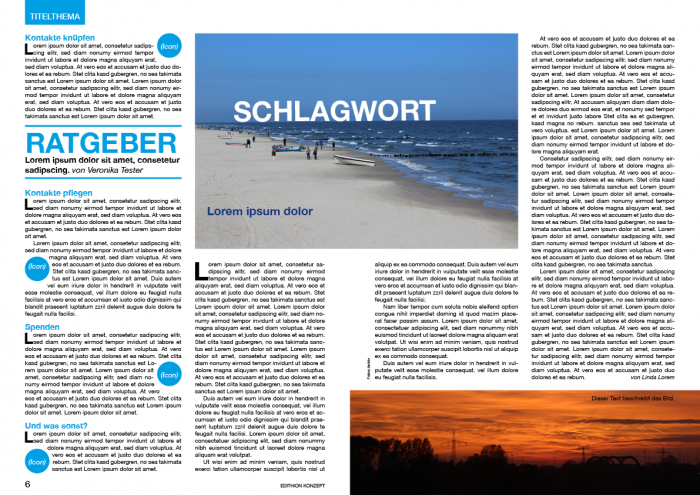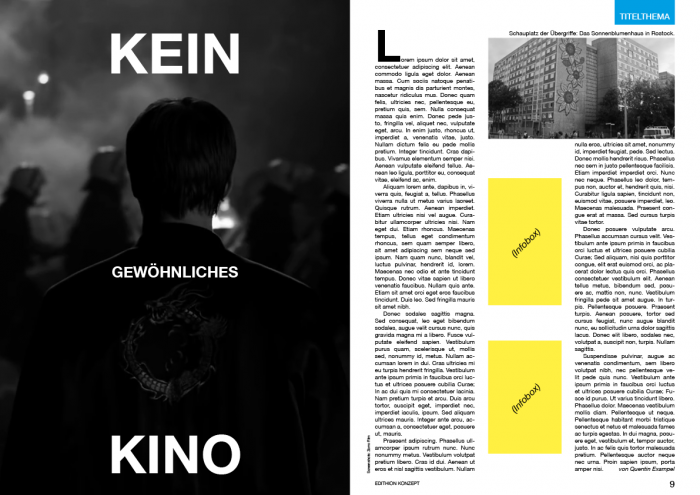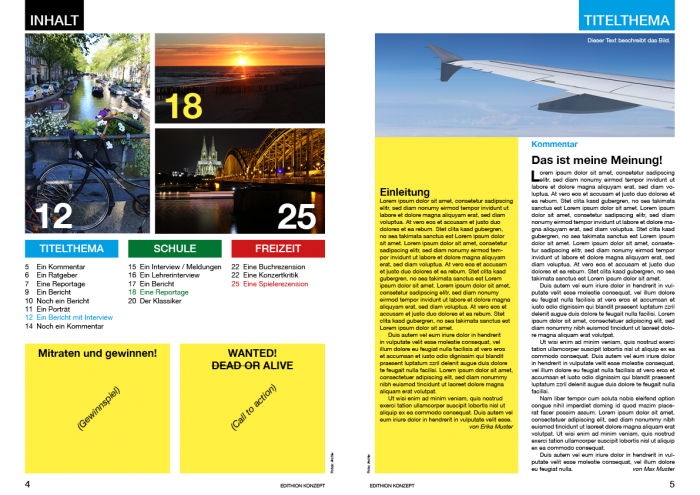
Typografie einer Schülerzeitung
ich mache seit etwas mehr als einem Jahr bei der Schülerzeitung unseres Gymnasiums mit und helfe da unter anderem beim Layout aus (derzeit noch mit tatkräftiger Unterstützung, bald dann ganz alleine *grusel*).
In letzter Zeit war es leider oft so, dass die neuen Ausgaben von ungefähr vier Leuten pro Klasse gekauft wurden, sich dann alle zusammen die "Bestseller-Rubriken" angeschaut haben und die eigentlich (sehr guten) Artikel keine Beachtung gefunden haben. Nur die Eltern hat’s interessiert...
Deswegen haben wir uns entschlossen, die ganze Schülerzeitung (insbesondere die Artikel) etwas aufwendiger und "zielgruppengerechter" zu gestalten. Bisher hatten wir ein Standardgerüst, in das die Texte dann mit InDesign eingesetzt wurden. Wir haben die Lato (https://www.fontsquirrel.com/fonts/LATO) für Überschriften und Segoe UI (diesen Microsoft-Standard - ja, ich weiß...) für Fließtext genutzt.
Ein paar typografische Grundkenntnisse habe ich zwar, bin mir aber relativ unsicher, was die konkrete Auswahl der neuen Schriftarten angeht.
Getreu unserem Ziel, der Zeitung einen ansprechenderen, flotteren Look zu geben, sollte die Schriftart frisch und fröhlich, aber auch aussagekräftig wirken; sich jedenfalls von dem aktuellen, eher neutralen, sauberen Aussehen abheben.
Ich finde, dass die Bree Familie (https://www.fontshop.com/superfamilies/bree) oder die Adelle-Familie (https://www.fontshop.com/superfamilies/adelle) recht gut passen würden.
Oder wären die zu "unseriös"?
Theoretisch brauchen wir zwei bis drei verschiedene Typen - für Überschrift, Untertitel/kürzere Texte und Fließtext.
Damit es nicht zu altmodisch aussieht, könnte man die Überschriften als (Slab) Serife und den Fließtext als Sans setzen.
Was meint ihr dazu? Welche Fonts würdet ihr nehmen? Ich bin gespannt auf eure Ideen und Anregungen!
Ich glaube ja nicht, dass allein die Wahl der Schrift das Layout modernisieren kann ... Zeig doch mal ein, zwei Doppelseiten Layout, damit man sich ein besseres Bild machen kann.
Oh, das ist ein tolles Thema! Ich habe früher auch mal eine Schülerzeitung mit entwickelt und am Laufen gehalten. Das hatte einen gar nicht unmaßgeblichen EInfluss auf die berufliche Richtung, die ich dann eingeschlagen habe. Ich würde genau wie Norbert gerne mal Beispielseiten sehen, dann fällt es viel leichter, etwas zur Schriftenauswahl zu sagen.  :-D
Ich glaube ja nicht, dass allein die Wahl der Schrift das Layout modernisieren kann ... Zeig doch mal ein, zwei Doppelseiten Layout, damit man sich ein besseres Bild machen kann.
Ich hatte vergessen, das nochmal genauer zu erwähnen: Natürlich wird auch die sonstige Gestaltung, also Seitenaufbau und -design erneuert. Die Typografie spielt dabei eine wichtige Rolle neben anderen Aspekten.
Entwürfe für den "Relaunch" haben wir gerade nur auf Paper, aber ich kann morgen mal versuchen, ein bis zwei Beispiele am Computer zu skizzieren.
Wie ihr seht, habe ich erstmal schnell ein paar Seiten am Computer skizziert. Sieht noch etwas sachlich und nüchtern aus, aber glaubt mir: selbst in dem Zustand wäre es eine deutliche Verbesserung zu vorher...
Wichtig zu wissen wäre noch, dass ich zur Vorschau alle Texte in der Helvetica gesetzt und mich in der Kürze auf InDesigns Standard-Farbfelder beschränkt habe.
Ein Urheberrechtshinweis: Das Bildmaterial von der 3. Doppelseite stammt aus dem Film, den der Artikel thematisiert ("Wir sind jung, wir sind stark", Zorro Film 2015).
Ich hoffe, ihr könnt mit dem Material etwas anfangen!
Meine ersten beiden Gedanken:
– Aha, keine Schülerzeitung, sondern ein Magazin
– Jessasmariandjosef, was für eine Bleiwüste
Jede Generation hat sicher seine eigene bevorzugte Form und Gestalt der Schülerzeitung, aber bei allen, die ich so erlebt habe, stand der nicht-professionelle Charakter der Zeitung besser zu Gesicht als der versucht-professionelle. Mir fehlt bei deinem Beispiel das Individuelle, für die Schule Charakteristische. Das, was ich sehe, ist leider beliebig austauschbar.
Ich wäre jetzt mal nicht so streng ... aber ja, besonders individuell sieht es natürlich nicht aus. Vielleicht ist das aber auch die Verführung der technischen Möglichkeiten; heute hat man auch als Schüler schon InDesign, wir hatten früher Schreibmaschine, Filzstift, Tippex ...
... derart mißverständlich? ...
Ja, sorry, kam leider bei mir irgendwie so an. Aber gut, dass du das noch mal komprimiert hast - denn da sind wir dann schon wieder ganz dicht beieinander.
... Oder irgendwas dazwischen: ...
Ich befürchte, für so was hat's einfach zu viel Text in einer Schülerzeitung. Aber die Idee, das nach »work in progress« aussehen zu lassen, finde ich ganz gut.